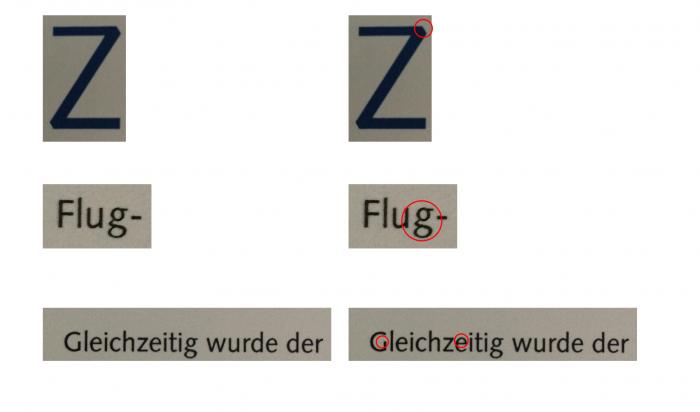
Hilfe benötigt: Welche Schriftart ist das?
ich bin auf der Suche nach folgender Schriftart. Kann mir da jmd. helfen?
Mir ist gerade aufgefallen, dass das R noch nicht passt - sonst sieht es aber ziemlich ähnlich aus. Gibt es noch Schriften, welche dieser sehr ähnlich sind?